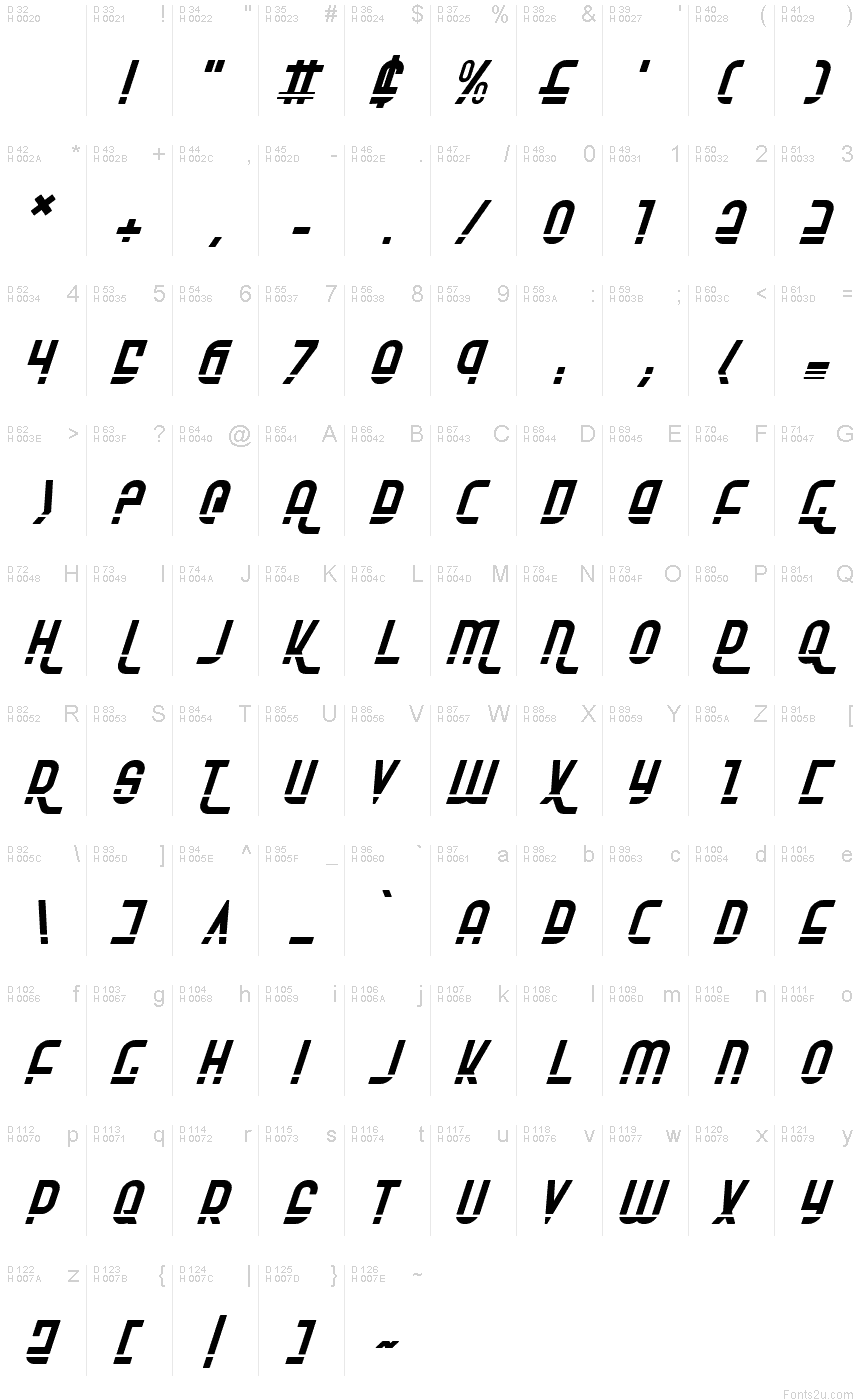
Ro'Ki'Kier Laser Italic od Iconian Fonts to darmowy krój typu display w stylistyce retro sci-fi, charakteryzujący się szybką, ściętą kursywą. Litery są mocno pochylone i wyciągnięte w ostre, geometryczne formy, a czyste, poziome cięcie biegnące przez cały zestaw nadaje mu charakteru rodem z ery automatów do gier i wypalonych laserem napisów.
Krój ten świetnie pasuje do plakatów, tytułów gier, okładek albumów, ulotek eventowych i znaków graficznych marek technologicznych, wszędzie tam, gdzie zależy Ci na dynamice bez utraty solidnej, blokowej formy. Jako darmowy font sprawdzi się również w tytułach, nagłówkach i krótkich tekstach, ponieważ powtarzający się środkowy podział nadaje nawet prostym słowom naładowany energią, futurystyczny rytm.
Ro'Ki'Kier Laser Italic od 2008 Iconian Fonts to darmowy kursywny krój typu display, zbudowany z mocno pochylonych wielkich liter i wyposażony w nacięcie w połowie wysokości znaku.
Projekt obejmuje szerokie klinowe kształty, ostre przekątne, powtarzalne cięcie oraz efekt przełamanej poprzeczki.